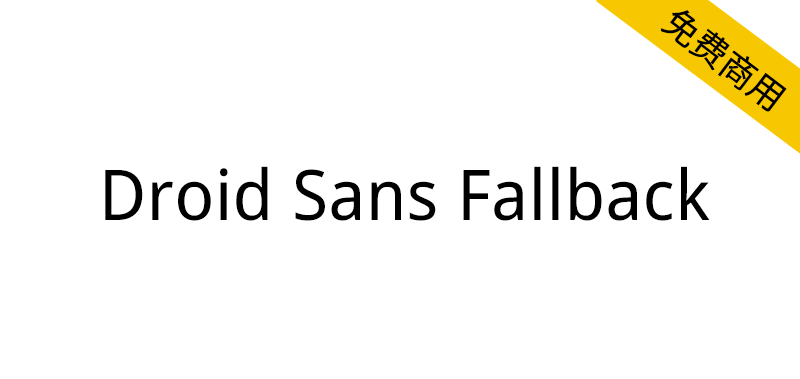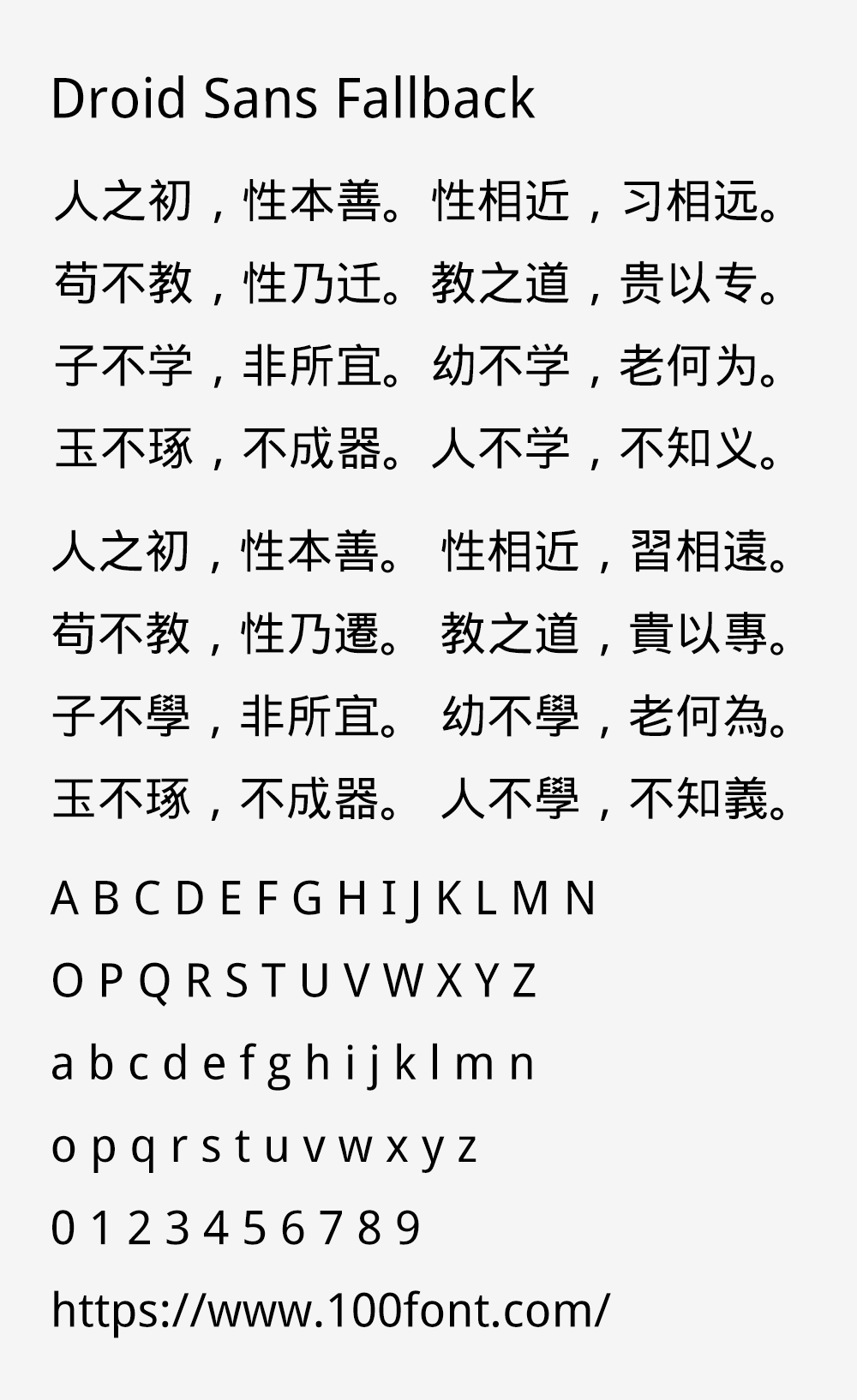
Droid Sans Fallback 是当年 Google 为推出 Android 设备时,委托台湾华康科技(威锋数位)为东亚各国字符设计的一款字体,承袭了 DFHeiW5-A 的设计风格,安卓手机默认中文字体,可免费商用。
根据 Ascender 字体公司的介绍,取名 Fallback 是因为 Droid Sans Fallback 是一款作为 Droid Sans 的字集补充而产生的字体,当系统在Droid Sans 找不到需要的字符时会 fallback 到 Droid Sans Fallback上。它采用了字体拼接技术,达到了 5W+ 的字符却还只有 4.31 MB。